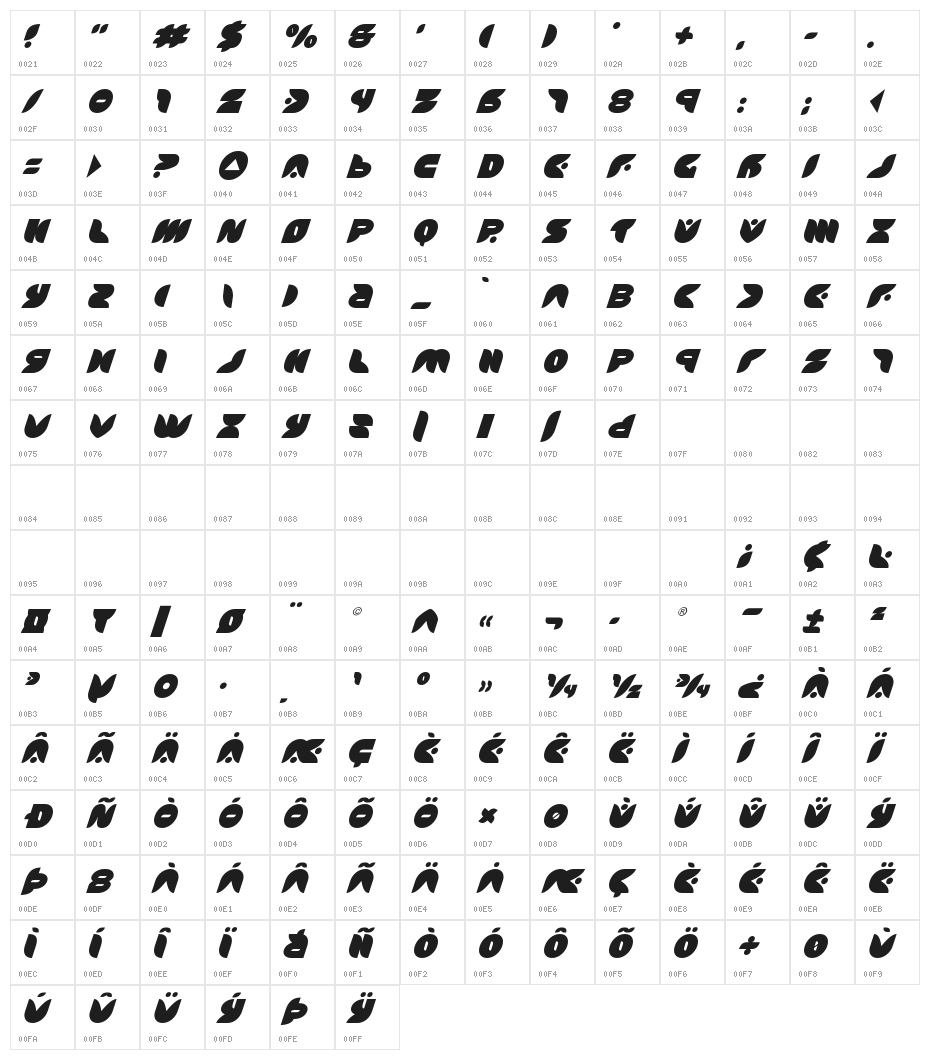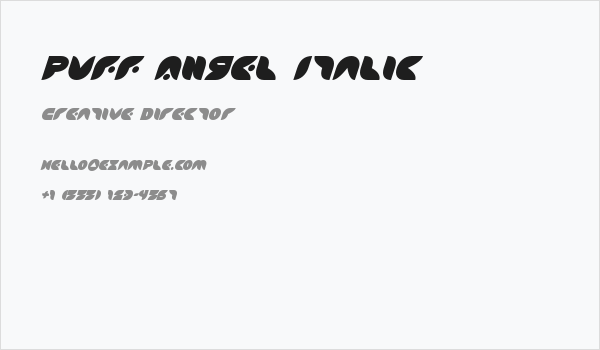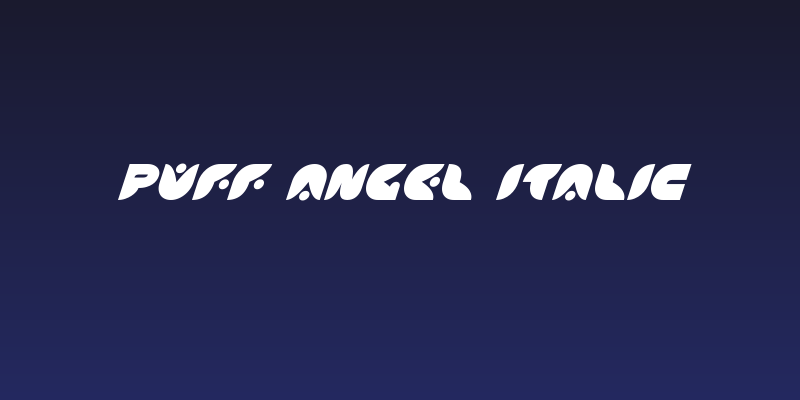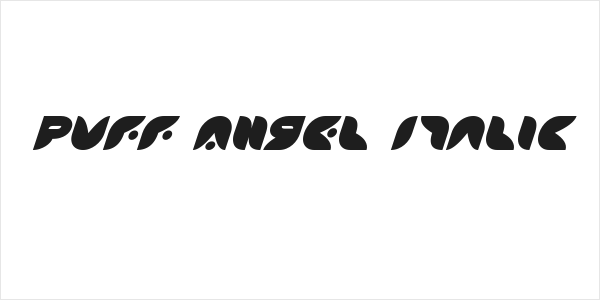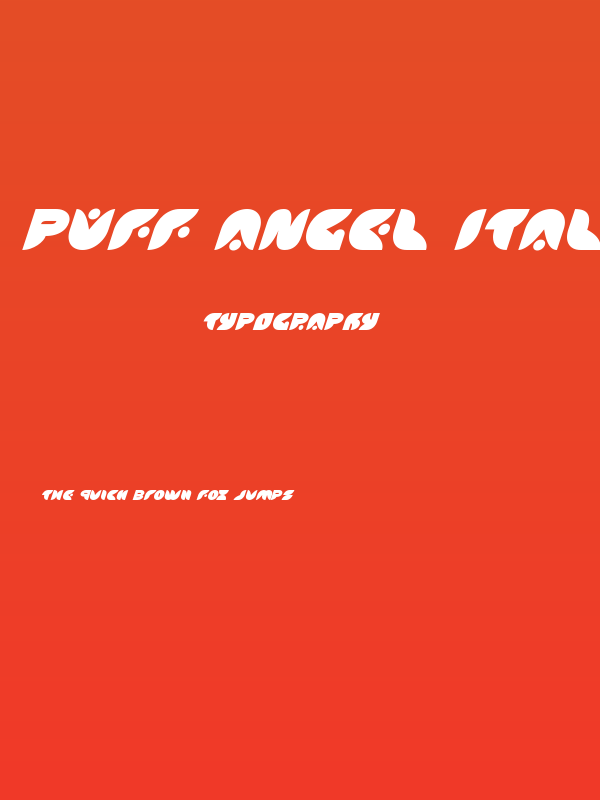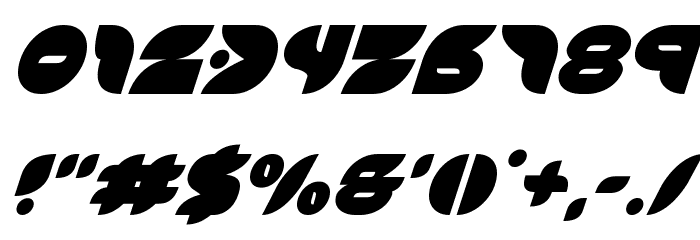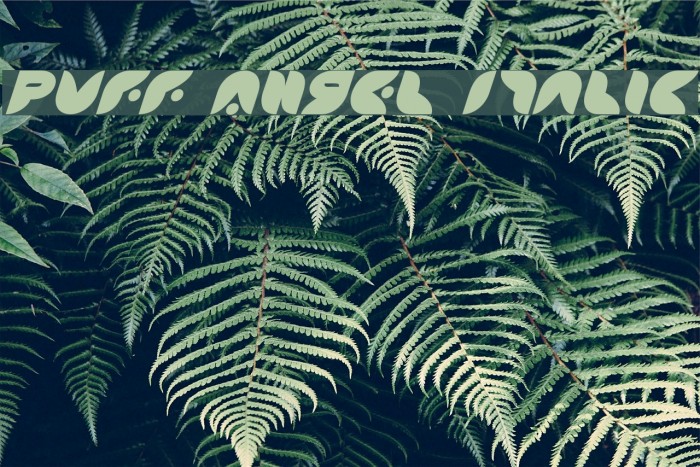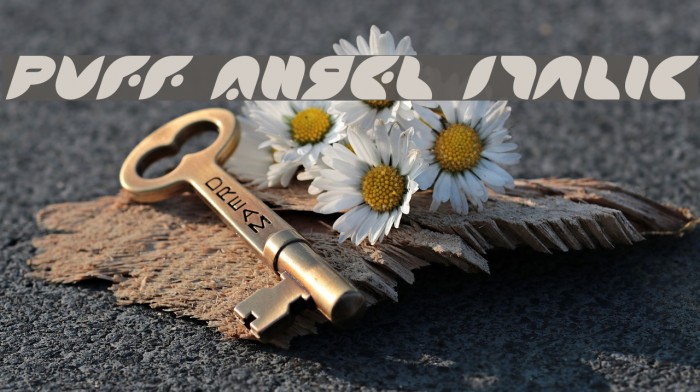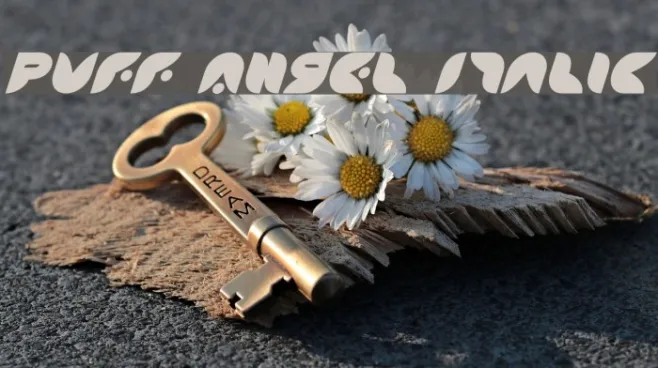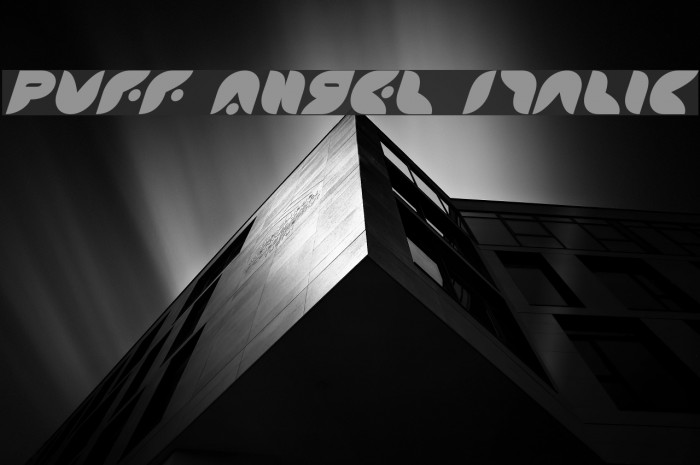
Puff Angel Italic Font
| Anwendungsfall | Logos, Headlines, Posters |
| Vorgeschlagene Projekte | Ideal for use in children's books, playful branding, posters, and creative digital content. |